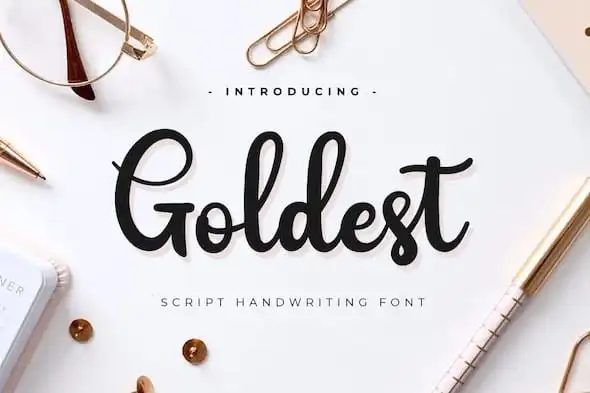
Goldest Script Font – Download Grátis
A Goldest Script Font é criada com precisão para atender a necessidade dos designers que desejam agregar charme, elegância e modernidade às suas criações. Embora a maioria das fóntes seja projetada para adicionar um toque de estilo ou personalização, a Goldest Script oferece algo mais: uma harmonia natural em cada design. Idealmente, é a fonte escolhida para aqueles que buscam um equilíbrio entre elegância e naturalidade nas suas criações. Ela foi projetada especificamente para complementar designs que precisam de um toque delicado do mundo da escrita à mão. A fóntes Goldest Script é uma fonte ideal para qualquer designer que busca agregar autenticidade sem sacrificar a modernidade, proporcionando aos designers um recurso gráfico poderoso e envolvente.